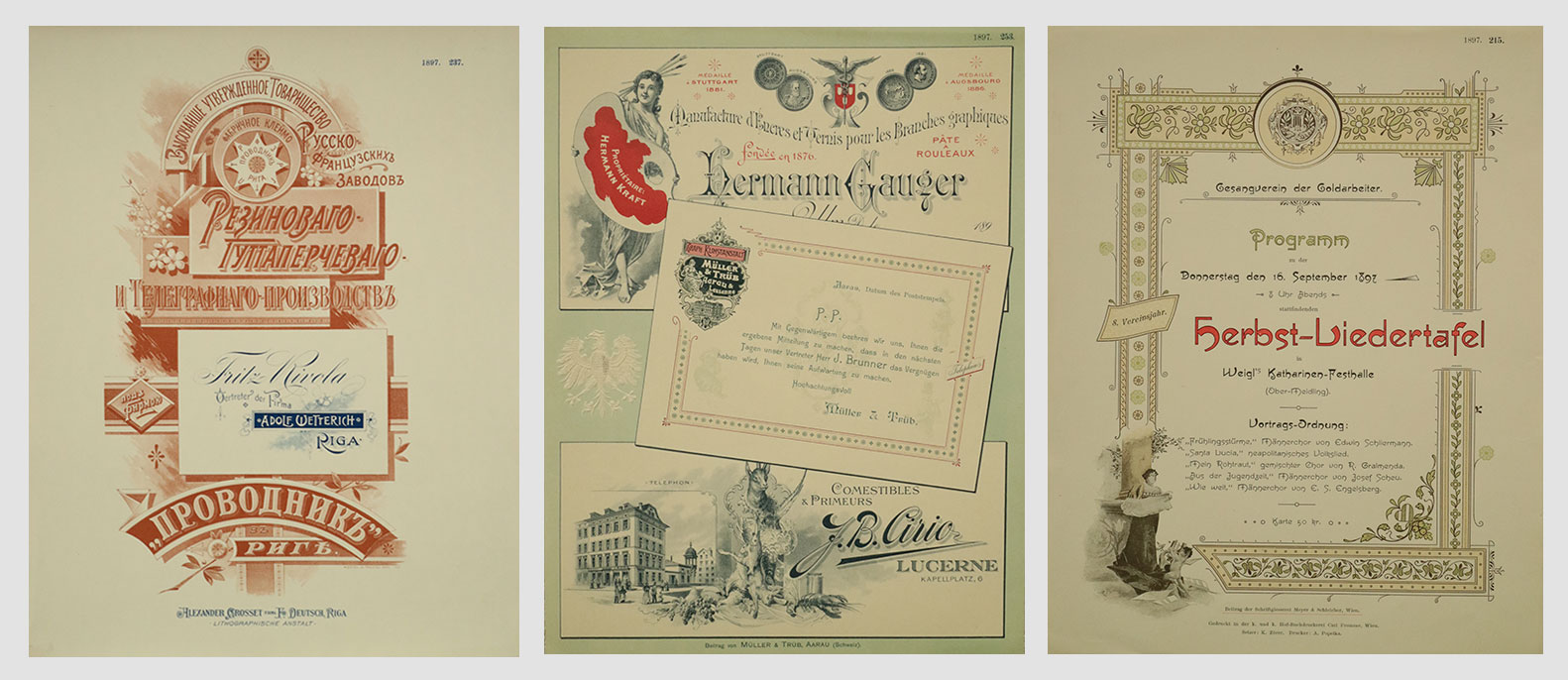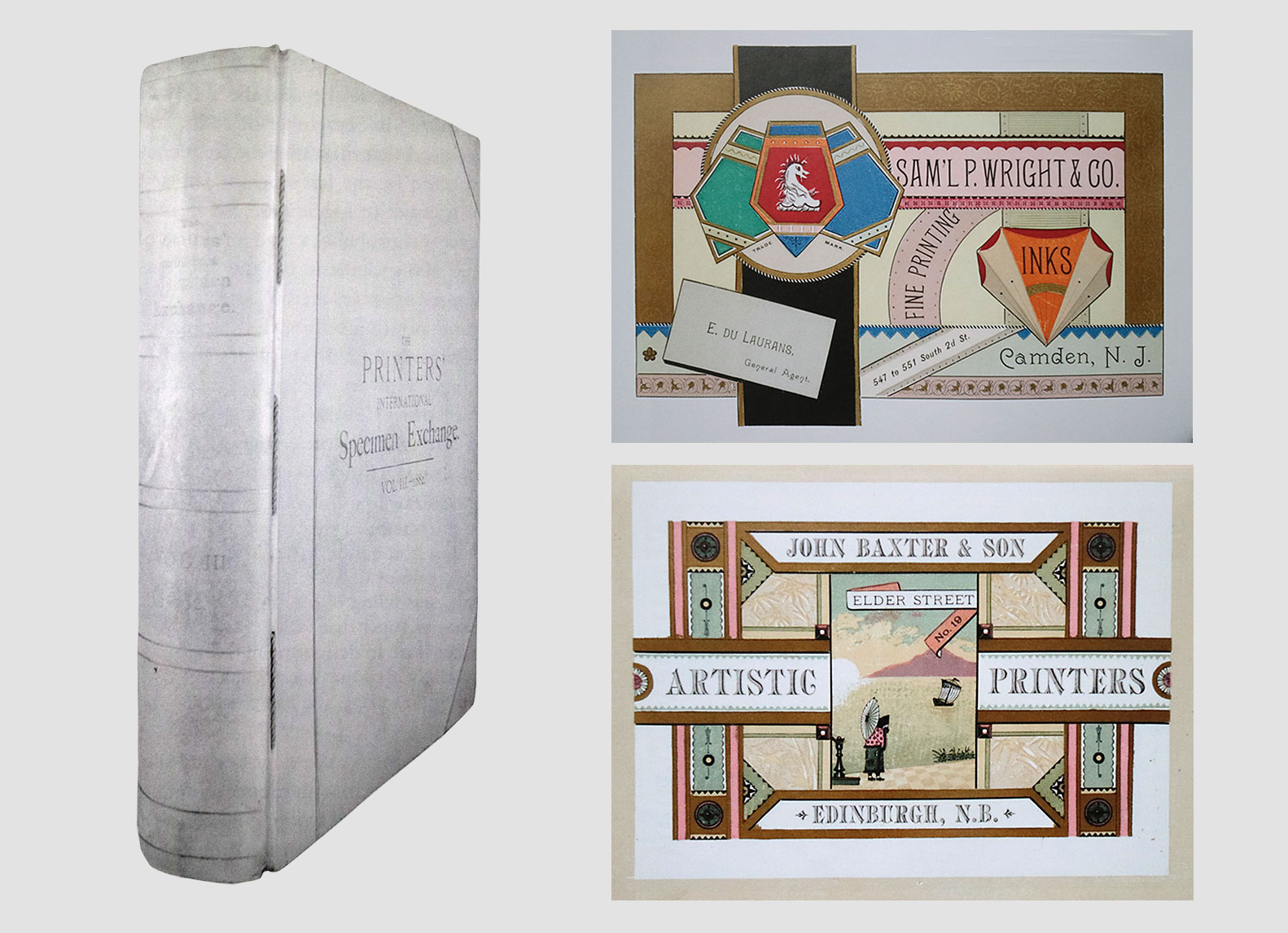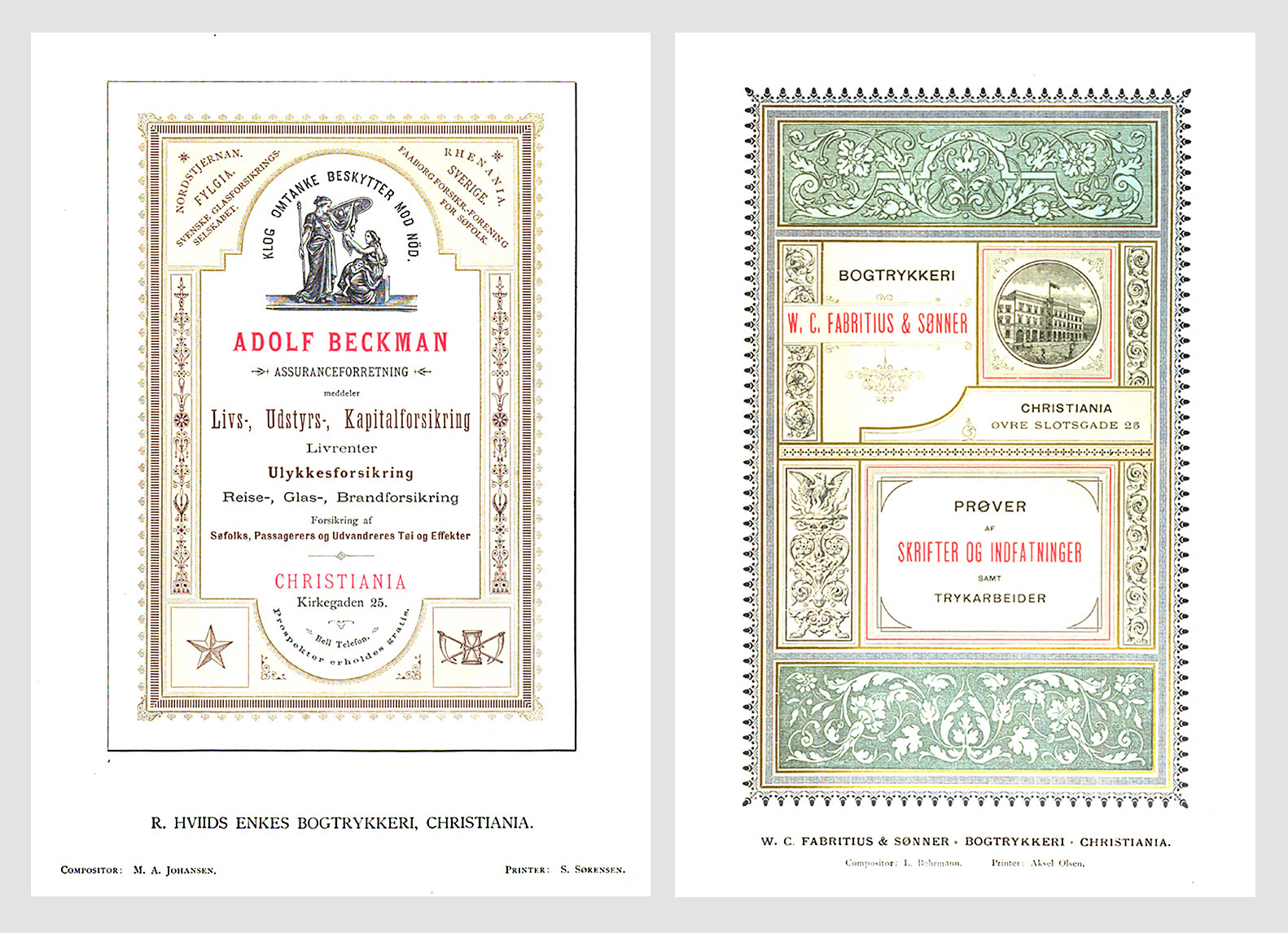
De grafiske fagene gjennomgikk i de to siste tiåra av 1800-tallet store tekniske og estetiske endringer. Det ble stilt kresne krav til trykksakenes utseende, og nye tekniske muligheter kom på løpende bånd. For å følge med i tida, byttet de beste trykkeriene i Europa og USA sine ypperste frambringelser seg imellom.
Årsaken til disse bytteordningene ligger likevel på mange måter paradoksalt nok i teknikkens begrensninger. Det var et behov for å studere andre trykkeres arbeid, men dette ønsket kunne ennå ikke oppfylles gjennom reproduksjoner i fagtidsskriftene og fagbøkene. Teknologiene som skulle gjøre tro gjengivelse av originaler på trykk mulig var fortsatt ikke oppfunnet, eller mangelfulle. Dette ikke minst for gjengivelsen av fargene, som var viktige i den typen trykksaker som sto i fokus som et vekstområde i denne perioden: forretningstrykksaker – såkalte aksidenser. Derfor måtte faglig interesserte utveksle sine originale arbeider seg imellom.
Norske trykkerier, samt deres settere og trykkere, var ivrige deltakere i dette mønsterbyttet. Og enkelte av våre trykkerier var helt på høyden med det som de store landene USA, England og Tyskland presterte, både teknisk og estetisk. Historien om de hittil ukjente norske mønsterbyttene blir her fortalt for første gang.
Betydningen av aksidenstrykkene
Siste halvdel av 1800-tallet var en periode da den grafiske industrien gjennomgikk store endringer og hadde sterk vekst. Litografien, der trykkbildet formgis for hånd med fettholdig farge på kalkstein, som det trykkes fra, uten det typografiske materiellets begrensninger, hadde tatt størstedelen av det voksende markedet for forretningstrykksaker. Men boktrykkerne kunne etter hvert ta opp konkurransen, som følge av mer nøyaktige trykkpresser, mer sofistikert typemateriell og bedre trykkfarger. Aksidenser – brevark, fakturaer, forretningskort o.l. – ble nå preget av svært komplekse satskomposisjoner, trykt i mange farger. Utøverne var entusiastiske over å kunne heve boktrykkerfaget til nye kunstneriske og tekniske høyder, og betegnet seg gjerne som «artistic printers». Innen århundreskiftet var den kjemigrafiske teknologien på plass, slik at man også kunne gjengi svart-hvitt illustrasjoner og fotografier, til og med i farger, på trykk. Den litografiske teknikken utviklet seg også, og oppnådde fremragende fargetrykk med chromolitografien.
Printers’ International Specimens Exchange bandt inn bidragene som en bok, her avbildet volum III. Øverst til høyre bidraget fra Cramer, Aikins & Cramer, Milwaukee, USA i volum VII. Under bidraget i volum IV fra Baxter, John & Son, Edinburgh i Skottland. Hentet fra The Rise and Fall of the Printers’ International Specimen Exchange. Klikk på bildet for større visning.
Det første mønsterbyttet ble startet i 1880 under navnet Printers’ International Specimens Exchange, og var opprinnelig en britisk-amerikansk idé. Noe av motivasjonen for bytteordningen var at de britiske trykkerne så at de amerikanske trykkeriene lå foran dem i kvalitet. Britene tok derfor initiativet, og mønsterbyttet ble organisert fra firmaet Field & Tuer i London, der Andrew Tuer også ga ut fagbladet Paper & Printing Trades Journal.
Medlemmene av mønsterbyttet sendte inn et større antall av et trykk de var stolte av og ville dele med andre, sammen med medlemsavgiften. I retur fikk de en innbundet samling av de innsendte bidragene. På denne måten fikk de se de ypperste frambringelsene fra store deler av den vestlige verden, og kunne inspirere hverandre. Å få et internasjonalt publikum for sine trykkarbeider må trolig ha sporet til fortsatt innsats.
Den første utgaven av mønsterbyttet, volum I, hadde 178 bidrag. Det skulle vokse til ca. 400 på det meste, og med økende utenlandsk deltakelse. I volum VIII var det til sammen 128 bidrag fra 17 land utenfor Storbritannia.
Norske deltakere i bytteordningene
To norske firmaer hadde bidrag i Printers’ International Specimens Exchange, nemlig Oslo-trykkeriene W. C. Fabritius og R. Hviids Enkes Bogtrykkeri. Fabritius deltok i sju utgaver, fra den femte (1884) til den sekstende og siste (1898), R. Hviids Enkes deltok i kun én, nemlig den sjette (1885).
To av de norske bidragene i Printers’ International Specimens Exchange. Til venstre R. Hviids Enkes Bogtrykkeris bidrag i Vol. VI (1885), til høyre W. C. Fabritius’ bidrag i Vol. VIII (1887). Klikk på bildet for større visning.
Fabritius-bidragene var nok initiert av Hermann Scheibler, men det var ikke bare han som sto for dem. Trykkerne J. Moe og Aksel Olsen og setter L. Behrmann er også nevnt som medvirkende til de fire bidragene jeg har sett. Men tyske Hermann Scheibler var i alt sitt virke en drivende kraft for kvalitet i norsk boktrykk. Han ble ansatt i bedriften i 1879 etter å ha fått et solid faglig grunnlag gjennom flere vandringsår som håndverkersvenn på kontinentet. Scheibler hadde en umettelig faglig interesse, og skulle sette et sterkt preg på norsk boktrykk framover. I 1885 ble han faktor i Fabritius, og i 1897 prinsipal (medeier og leder).
R. Hviids Enkes Bogtrykkeris bidrag er signert setteren M. A. Johansen og trykkeren S. Sørensen. Denne Johansen er Morten Johansen, som hadde vandret og arbeidet i Tyskland fra 1873 til 1877. I Dresden traff han den ovenfor nevnte Hermann Scheibler, og det var Johansens fortellinger om Norge som hadde vakt Scheiblers lyst til å reise hit. Morten Johansen ble ansatt som faktor i R. Hviids Enkes Bogtrykkeris aksidensavdeling i 1879. Han overtok bedriften i 1889, nå under navnet Morten Johansens boktrykkeri. Noen år seinere tok han de viktige initiativene som førte til innføringen av tvungne svenneprøver og fagskole i boktrykkerfaget.
De norske bidragene jeg har sett har et historisk preg, jfr. Fabritius’ bidrag avbildet over. De benytter skriftstøperienes rammer og flatestykker med renessansemotiver, gjerne arrangert i en arkitektonisk preget løsning. Bidragene i Printers’ International Specimens Exchange spente på sett og vis mellom to ytterpunkter. Det ene med en viss tilknytning til boktrykkets tradisjoner, manifestert gjennom en tradisjonell symmetri og bruk av stilhistoriske dekorative elementer. Det andre ytterpunktet var friere, løsrevet fra tradisjonen, ofte regelbrytende, der elementer f.eks. kunne være skråstilt og plassert asymmetrisk: det man kalte «artistic printing». Mitt inntrykk er at denne sistnevnte retningen, som man i Norge kalte «den frie retning», ikke fikk betydning hos oss før på slutten av 1890-tallet.
KVALITET FRA NORSKE BOKTRYKKERE
De norske bidragene til de internasjonale grafiske bytteordningene av aksidenser (det vil si forretningstrykksaker) i de siste tjue åra av 1800-tallet, viser at flere norske trykkerier var fullt på høyde med de beste utenlandske trykkeriene, både teknisk og estetisk. Aksidenstrykk fra denne perioden har ikke blitt verdsatt høyt sett med ettertidas estetiske øyne, men omfattes i dag av en økende interesse. Med datidas tekniske muligheter i mente avkrever de utvilsomt beundring. Som uttrykk for hva bidragsyterne anså som sitt ypperste arbeid, er de av stor interesse for den grafiske historien. Jeg er derfor interessert i kontakt med alle som har tilgang til utgaver av den britiske eller den tyske mønsterbytteordningen – dette for å kunne fotografere de norske bidragene. (Avbildet over er boksen som inneholder bidragene til 1897-utgaven av Internationaler Graphischer Muster-Austausch des deutschen Buchdrucker-Vereins.)